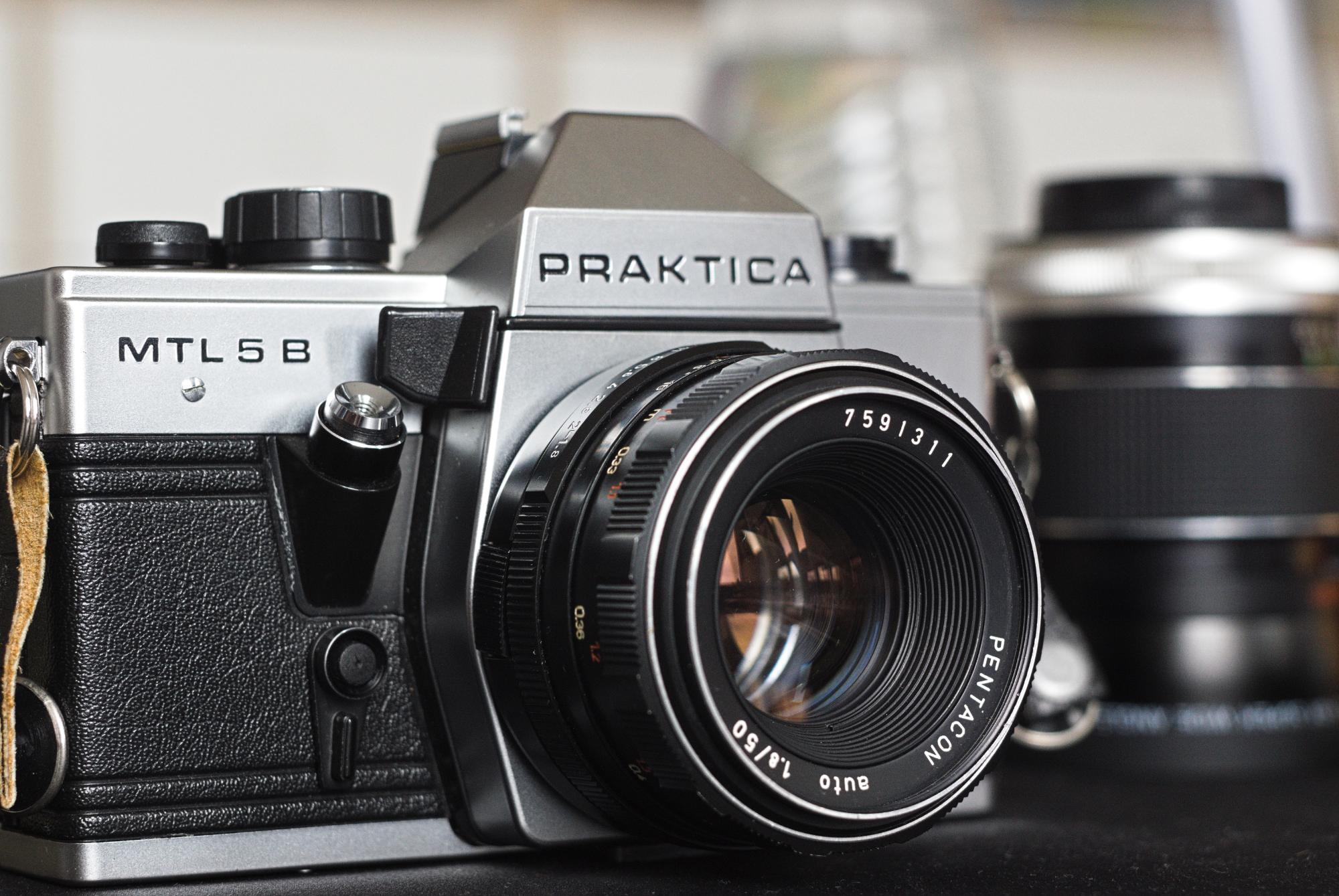
Welche Schriftart gehört zur Praktica (DDR Kamera)?
ich habe mal ein Foto einer Praktica Kameras gemacht und frage mich, welche Schriftart dort der Schriftzug "Praktica" oder auch die Modellbezeichnung hat. Bei meiner Recherche bin ich bisher zur Microgramma gekommen, die sehr nah dran ist, aber nicht 100% deckungsgleich. Der untere Teil der Buchstaben fällt bei der Praktica etwas kürzer aus.
Der Schriftzug der Praktica war auf den beiden Fotos auch leicht unterschiedlich, mich interessiert aber primär der Schriftzug des jüngeren Modells.
Die Eurostile weicht meiner Meinung nach mehr ab, die Microgramma scheint da noch am passendsten. Gedruckt gibt es das Logo auch auf neueren Produkten, und auf deren Homepage als Logo:  logo_200x.png?v=1613159768
Aber abgesehen von dem Logo und der Modellbezeichnung finde ich die Schriftart nirgends anderswo verwendet vom VEB Pentacon. Also auch in der Bedienungsanleitung der Kamera findet die Schriftart nicht mal für Überschriften oder so eine Anwendung. Ich glaube, ich gehe dann erstmal mit Microgramma als Lösung, mit Vorbehalt. 🙂
Laut Wikipedia wurde die Eurostile dann aber für die Beschriftung der Carl Zeiss Jena Objektive genutzt, wo natürlich die Verwandtschaft besteht, somit bin ich zuversichtlich, dass wir hier richtig liegen.